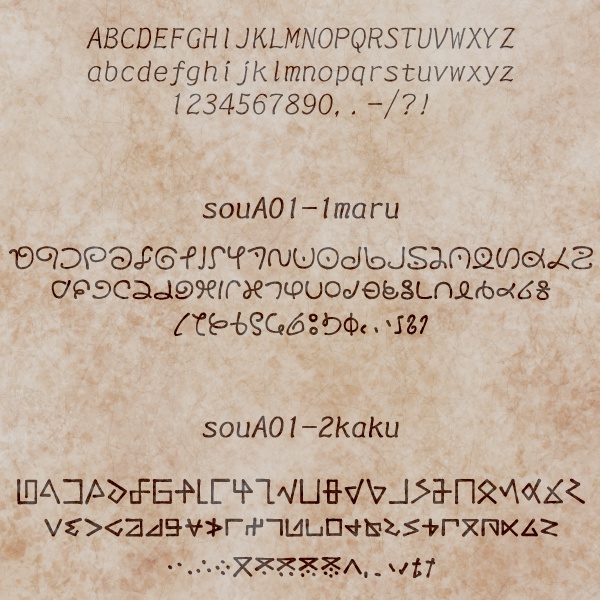
異国語・呪文フォント「souA01」
CLIP STUDIO ASSETSで配布している「文字ブラシ4」を フォント化したものです。 アルファベットをベースにした、未知の言語っぽい文字列を 作成するためのフォント(OpenTypeフォント)です。 書体は丸みを帯びたタイプ(maru)と直線タイプ(kaku)の2種です。 【注意事項】 著作権は放棄しておりません。 意匠・商標登録などに使用することはご遠慮ください。 フォントデータの販売・再配布もご遠慮ください。 その他の使用についてはご自由に。 また、当フォントの使用により損害などが生じても、 一切の責任を負いませんのでご了承ください。 【タイプ可能な文字】 ABCDEFGHIJKLMNOPQRSTUVWXYZ abcdefghijklmnopqrstuvwxyz 1234567890,.-/?!